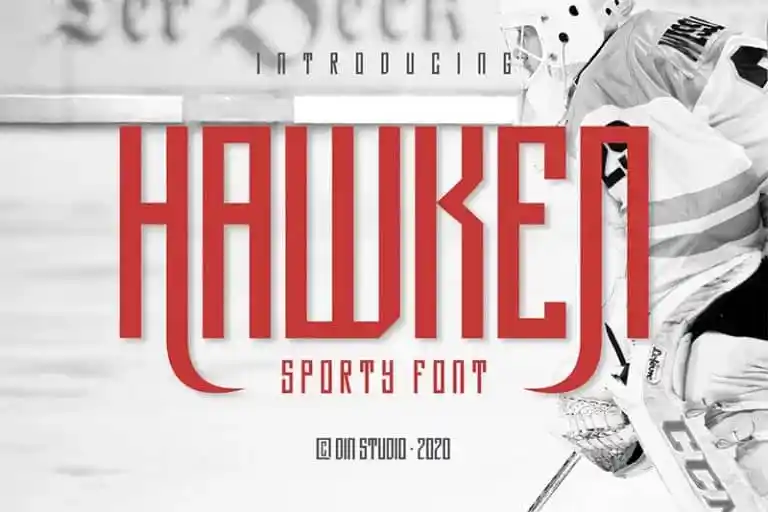
Hawken Display Font é uma fonte tipográfica clássica desenvolvida para aplicar a esportes. Perfeita para qualquer projeto profissional que envolve este tema, esta fonte é um tipo de sans serif poderoso criado pela Din Studio. A sua elegância e robustez tornam-na ideal para elementos visuais como citações, posters, logotipos ou marcações, cartões de visita, necessidades de artefatos manufaturados, impressões, camisetas, tênis de mesa, pranchas de surf ou embalagens. Sem dúvida, Hawken Display Font é uma escolha perfeita para tornar qualquer projeto um verdadeiro destaque na cena dos esportes.